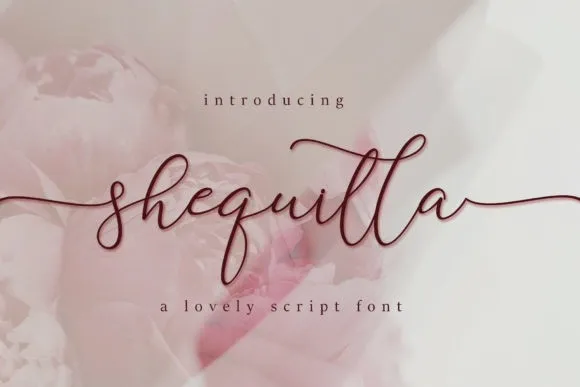
A Shequilla Font é uma tipografia casual criada pelo designer tinyhandletter, com traços limpos e alta contraste, que destacam a elegância de seu desenho. Esta fonte PUA (Personal Use Allowed) permite ao usuário acessar todas as gálias e swashes sem grandes dificuldades. Perfeita para quem busca uma fonte casual e sofisticada, ela irradia um toque delicado que tornará suas criações ainda mais atraentes e vivas. Descubra o encanto desta fonte e faça sua arte ganhar destaque com esta elegância inconfundível.